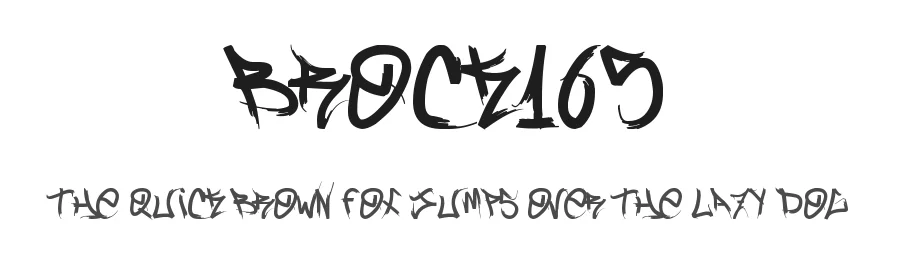
About Brock Vandalo Font
Brock Vandalo Font is a script font that shines as a display or heading face. Pair it with a clean sans-serif or serif font for body text β the contrast creates a clear hierarchy while the two styles stay balanced and easy to read.
Brock Vandalo Font